【インタビュー】児童書の老舗・ポプラ社が追求してたどり着いた「子どもファースト」なフォント選び
「かいけつゾロリ」や「おしりたんてい」「ズッコケ三人組」「少年探偵団」…いつの時代も子どもたちに人気の児童書出版で知られるポプラ社。そのポプラ社が「こどもの学び」の新しいサービスに取り組んでいます。
そんな新サービス、「Sagasokka!」になんとモリサワのUD新ゴが採用されているんです!今回は開発メンバーの皆さんに、開発経緯やフォントへのこだわり、UD新ゴを採用した理由について伺いました。
1.コロナ禍がきっかけ? 児童出版社がデジタルコンテンツを展開した理由
老舗の児童書出版社であるポプラ社は、2022年4月に本と学びのプラットフォーム「MottoSokka!」を立ち上げ、調べ学習応援サービス「Sagasokka!」と、電子書籍読み放題サービス「Yomokka!」の提供を開始し、教育ICT業界に本格参入しました。
―ポプラ社さんといえば、子供たちに人気の書籍を多数出版している児童出版社というイメージですが、今回デジタルコンテンツである「Sagasokka!」を開発したのにはどういう経緯があったのでしょうか。
北野:弊社では2006年より15年以上にわたって、図書館や学校の図書室の端末で百科事典を検索できる「ポプラディアネット」という教育機関向けWebサービスを提供してきました。ところが、2020年4月の緊急事態宣言に伴う休校措置で、子どもたちが利用できなくなってしまったんです。
契約校からは「なんとか家でも使えないか」と相談が寄せられました。その時点で端末を配布していた学校もあったのですが、肝心のコンテンツの供給が追いついていなかったんですね。それであれば、私どもも開発を急がなければならないということになりまして。
ー コロナ禍の影響で、図書館や学校に設置してある既存端末で提供されていたWebサービスが、子どもたちに届けられなくなってしまったことがきっかけの1つだったのですね。
勝又:そうなんです。コロナ禍により、GIGAスクール構想(※1)による「1人1台端末」の前倒しが決定していたので、まずはそこに間に合わせようと、半年間で電子書籍読み放題サービスの「Yomokka!」を開発して、2021年4月より1年間は無料トライアルの形で提供しました。
同時進行で「Sagasokka!」の開発を進め、2022年4月に「Yomokka!」の有償化と同じタイミングで正式にリリースしました。
(※1)GIGAスクール構想…児童生徒向けの1人1台端末と、高速大容量の通信ネットワークを一体的に整備し、多様な子どもたちを誰ひとり取り残すことなく、公正に個別最適化された創造性を育む教育を、全国の学校現場で持続的に実現させる構想
―では、どちらのサービスもGIGAスクール構想を受けて開発されたものだったんですね。
勝又:はい。私たちは出版社なので、子どもたちが文房具と同じように端末を使うようになれば、相対的に紙の本に触れたり読書にかけたりする時間が減っていくだろうという危機感がありました。ですので、サービス開発の原点には、本を起点にしたコンテンツを学校の端末に入れてもらうことで、子どもたちが本に親しむ機会を増やしていきたいという思いがあります。
2. 「子どもたちも1人1台」時代のコンテンツに求められるものとは?
―「Sagasokka!」はどのようなサービスですか?
北野:「Sagasokka!」は10年ぶりの大改訂を経て昨年秋に第三版が刊行された「総合百科事典ポプラディア」のデジタル版を搭載する「ポプラディアネット」の後継サービスです。検索機能だけでなく、トップページにはクイズやコラムを設けて、子どもたちの「知りたい」「なんだろう」という気持ちをアクションにつなげ、そこから百科事典に触れられる作りになっています。
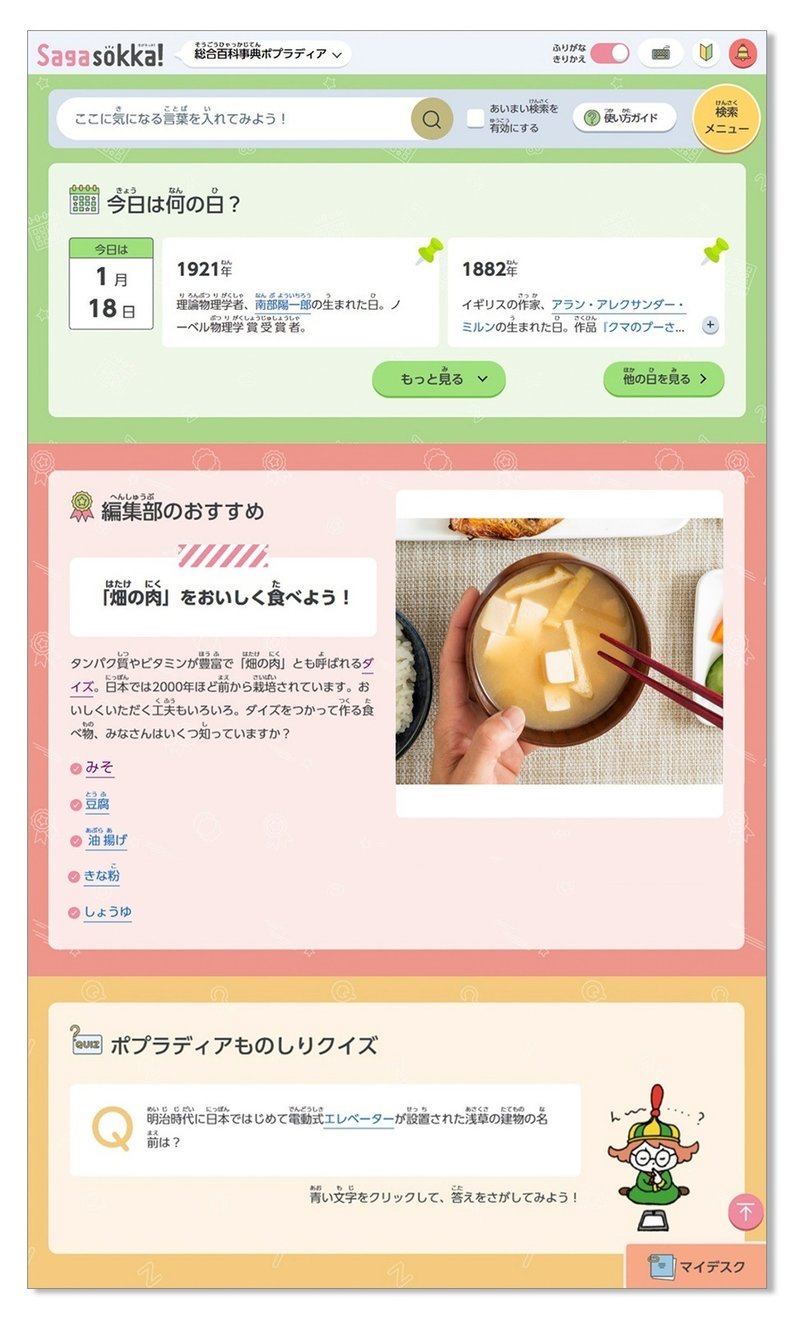
杉山:子どもたちに興味を持ってもらう、好奇心の入り口をたくさん作ってあげる、というところが大きなポイントになっていて。
北野:単に先生に促されて調べるだけだとそこで終わってしまいますよね。子どもたちが毎日アクセスして、あちこち寄り道をしながら自分の知りたいことや好きな分野と出会うことができる、というのがサービスの基本コンセプトです。
ー子どもたち自身の興味や好奇心を刺激する、受け身にならない学習体験を目指しているんですね。デザインやレイアウトで工夫したことはありますか?
北野:レイアウトは昔ながらの3カラムから、タブレットで見やすい形に変えました。ボタンを判別しやすい色合いにするなど、ロービジョン(※2)の方の見え方にも配慮していますが、AA(※3)の完全準拠レベルまで突き詰めてしまうと障害のない人にとってはコントラストが強すぎてしまうので、ちょうどいい落としどころを探すのにかなり苦労しました。
(※2)ロービジョン…視覚に障害があり日常生活に支障をきたしている人
(※3)AA…アクセシビリティの達成基準レベル
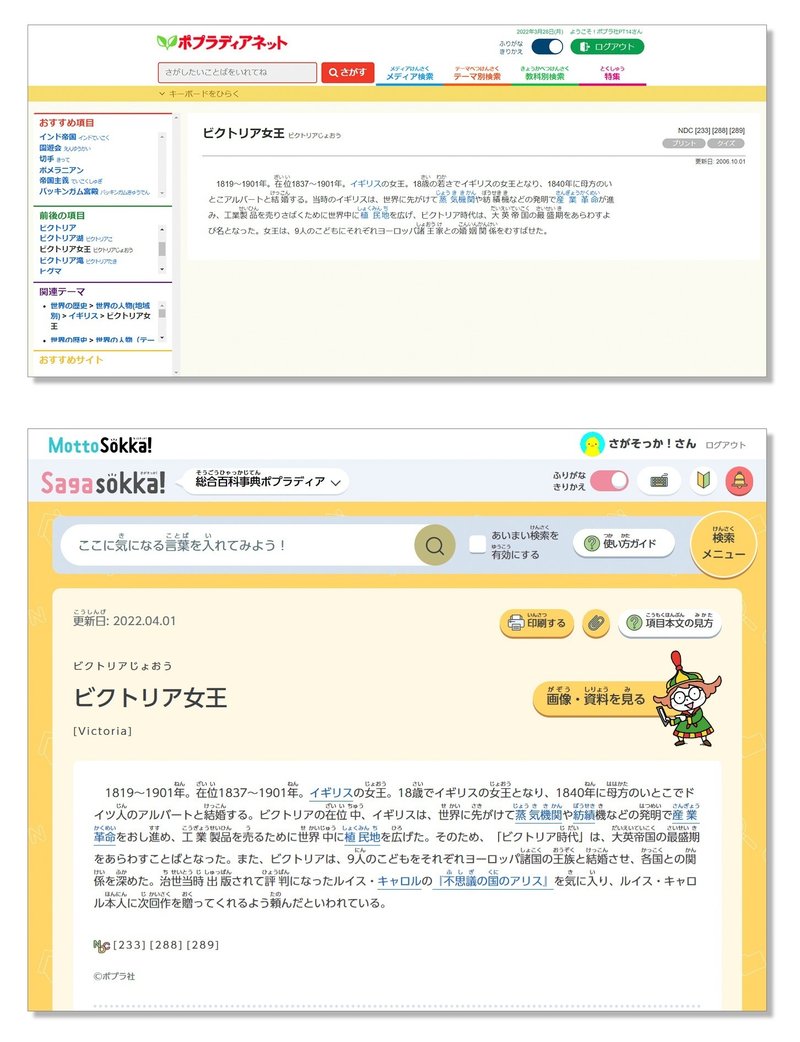
上:ポプラディアネット
下:Sagasokka!
杉山:アクセシビリティ(※4)の観点から、誰にとっても使いやすいデザインを意識しています。例えば、集中力が継続しづらいお子さんのために、点滅するボタンなど強く注意をひくものを置かないようにしています。一方で、活用してもらうためには押したくなるようなデザインにしないといけない。いまだに試行錯誤中ですが、そのあたりのバランスは本当に難しいですね。
(※4)アクセシビリティ…身体の機能や年齢、閲覧環境の違いを問わず、情報やサービスを利用できること
ー子どもたちも自分の端末を自分だけが使う「1人1台」の時代だからこそ、検討しなければない部分があるんですね。
3. 迷ったら直接聞いてみる!「子どもファースト」のフォント選び
―「Sagasokka!」にはUD新ゴをWebフォントとして採用いただきました。フォントはすぐに決まったのですか?
杉山:フォント選びにはかなり時間をかけましたね。子どもたちが自分から触りたくなるような、親しみの持てるデザインが要件でしたので、そのイメージに合うものを検討しました。チーム内ではUDフォントを使う意向が固まっていたので、何パターンかのフォントを項目本文の画面に当てはめたサンプルも作成しました。
北野:書籍版の「ポプラディア」では、第三版から項目本文のフォントをUDデジタル教科書体とし、圧倒的に読みやすくなったんです。やはりフォントの力は大きいなと感じていたので、Web版でもそのままUDデジタル教科書体を使うつもりでいたんですが、PCやタブレット画面上で見ると少し印象が違っていました。
UDデジタル教科書体を採用
杉山:UDデジタル教科書体は、目に優しいからこそ強弱がないというか、トップページも項目本文も同じフォントを使う方針だったので、親しみやすさの点ではもう少しポップで柔らかいフォントのほうがいいのかなと感じました。
北野:「Sagasokka!」のロゴとの親和性もありますしね。
杉山:同じフォントでも紙とデジタルで見え方が変わるのは意外でした。それで、社内の候補はある程度絞ることができたのですが、「大人が見やすいと感じていても、実際に使う子どもたちはどうなんだろう…」と思い、子どもたちにアンケートをとってみよう!ということになったのです。
―教材開発時に教員へのヒアリングをすることはあっても、子どもたちに直接聞くケースはなかなかありませんよね。
杉山:ちょうど学校にうかがう機会があったのでチャンスだなと(笑)。学校側に協力していただいて、3年生から6年生までの児童と先生方に用意した端末の画面を見せ、見やすい文字を投票してもらいました。
子どもたちは普段フォントを気にして見ているわけではないので、「文字の形が違うってどういうこと?」と、はじめは理解できないんですよ。でも違いに気づいた後は一生懸命答えてくれました。中には “推しフォント” を熱く主張する子もいたりして(笑)。
―その子にはぜひモリサワフォントのファンになっていただきたい(笑)。まさに現場の生の声ですね。
杉山:アンケートの結果を受けて、社内でもさまざまな角度から再検討した結果、UD新ゴを採用することにしました。硬すぎず幼すぎずのバランスのよさも決め手でしたね。
北野:デザイン時のペルソナ(※5)が小学6年生の元気な男の子「たつや君」だったので、ゲームやお菓子のパッケージなど身近な商品にもよく使われているUD新ゴは、そういう子たちにとって親しみやすいのではないかと、満場一致で決定しました。
(※5)ペルソナ…自社製品・サービスの対象となる架空の人物像
―これまでのお話から、皆さんのフォントへの強いこだわりを感じます。子どもの視点を重視する点は、長く児童書を手掛けてきた御社ならではのスタンスかもしれませんね。
北野:そうですね。ずっと「迷ったときには子どものことを考えよう」という意識はありました。
杉山:「Sagasokka!」ユーザーとして想定しているペルソナ「たつや君」ならどっちを選ぶかな、と(笑)。
―UD新ゴを採用した理由のひとつに、Webフォントで使えることを挙げられていましたが、その理由は?
岡野:「Sagasokka!」は百科事典ですから非常に文字量が多いんですが、中でも特大項目と呼ばれるもの、例えば「アメリカ合衆国」ですね。概要、目次、本文の説明と、これだけのボリュームを項目ごとにわかりやすく表現するにはウエイトなどを変えてWebフォントで表現することが必須でした。
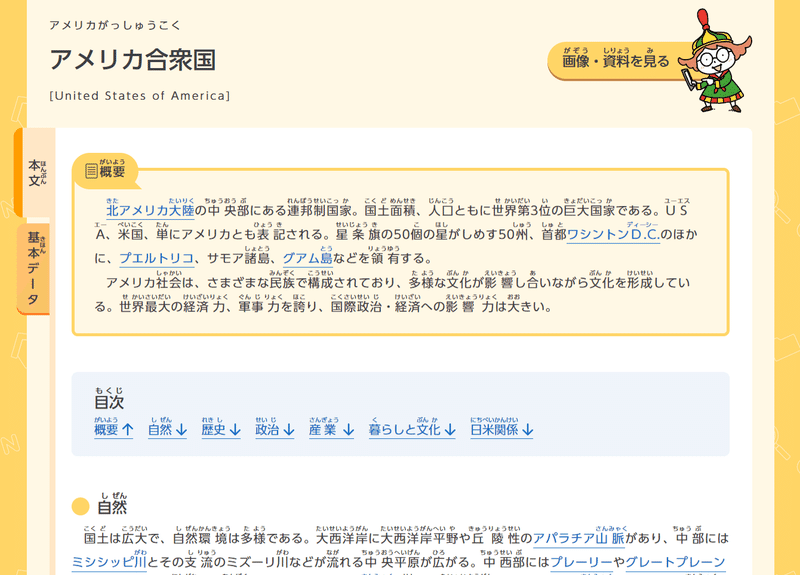
―文字数の多いページを表示する際、Webフォントだと「重くて遅い」イメージを持たれたこともありますが、実際はどうでしたか?
岡野:非常にスムーズで、ストレスや違和感なく使えました。
実装に関しても問題なく行えましたが、気がかりだったのは収録文字数ですね。今後はさらにコンテンツを増やしていこうと考えているので、文字がどこまでカバーされているかは一番気を使いました。
「Yomokka!」と「MottoSokka!」はUD新丸ゴを採用していますが、「Sagasokka!」ではUD新丸ゴよりも文字数が多いUD新ゴに決めました。
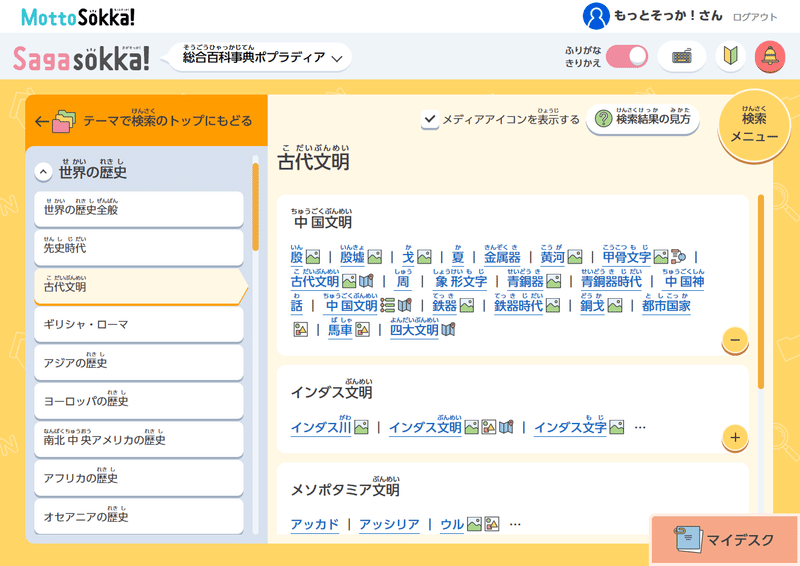
―カバーされていない人名や地名に使われている異体字などにはどう対応されているんですか。
岡野:画像で対応していますが、ほとんどの文字がカバーされているので、画像で作成したものは多くありません。
北野:画像になってしまうと、検索に対応しないというデメリットがあるのですけれど、「Sagasokka!」では表示できる文字が飛躍的に増え、全文検索の精度も上がりました。
岡野:画像で作成したものは、具体的には音楽の記号や、数学のxyくらいですかね。
北野:学習系のコンテンツを提供している身としては、おいそれと譲れない文字の形や記号があるんですね。「絶対に普通のxやyでは嫌だ」っていう(笑)。そこはこだわっています。
北野:「Yomokka!」は使うたびにポイントがたまる機能など、さまざまな仕掛けを設けているんですが、「Sagasokka!」に関してももっと楽しみながら使っていける機能を追加していけたらいいなと話し合っているところです。今後は「ポプラディア」だけでなく「ポプラディアプラス」シリーズなど、コンテンツの追加も考えています。
勝又:「Yomokka!」も「Sagasokka!」もユーザーの方の声を取り入れた本格的なサービス改善はこれからですが、「Yomokka!」は来年の夏以降、大きなデザインのリプレイスを考えています。デジタルだからこそできる挑戦を、各チームで今後も続けていきたいですね。
―「子ども」を主語にして話す皆さまの様子から、開発にかける真摯な思いと、フォントが持つポテンシャルへのこだわりを感じました。